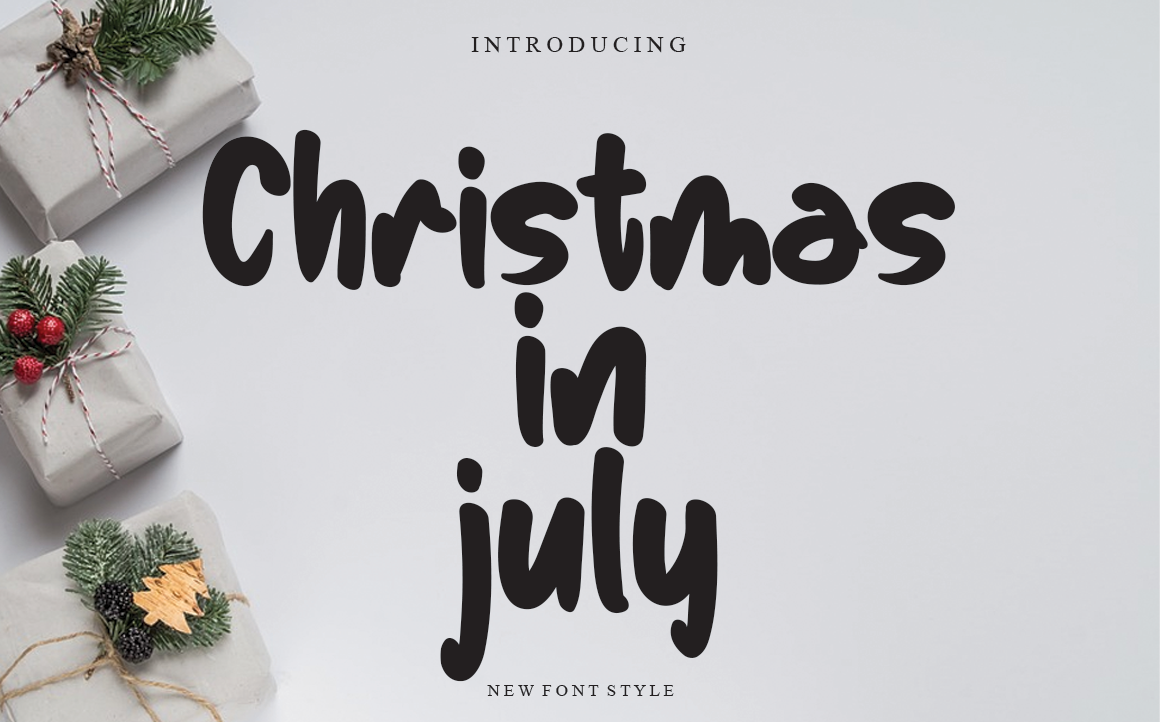
Christmas In July Font – Fonte Grátis
Christmas In July Font
Esta é uma fonte escrita à mão única e divertida, ideal para quem quer dar uma personalidade a qualquer projeto criativo. Se você está procurando por uma fonte perfeita para Instagram ou uma script de calligrafia para um projeto DIY, essa fonte irá transformar suas ideias em verdadeiros trabalhos de arte! Ideal tanto para aqueles que buscam uma nova maneira de expressar-se digitalmente quanto para designers que desejam dar um toque especial a qualquer projeto. Seja você um criador digital ou um decorador de interiores, esta fonte escrita à mão certamente fará parte da sua coleção de recursos gráficos indispensáveis.